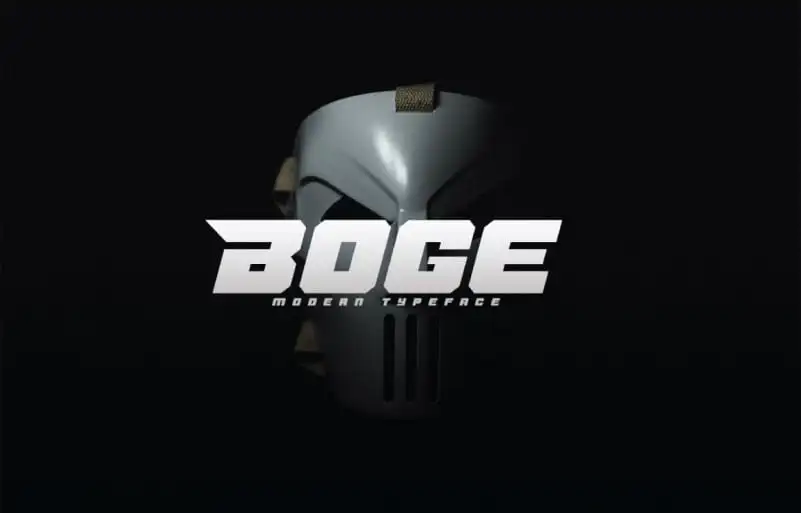
Boge Display Font – Download Grátis
Boge Display Font é uma elegante seleção para aqueles que buscam adicionar um toque distinto a seus projetos digitais. Esta fonte em estilo display é notável por seu traço bold e itálico, com ângulos aguçados que criam efeitos dinâmicos e vibrantes. Com ligaturas personalizadas, esteve concebida para fornecer inúmeras possibilidades de design, sendo especialmente apropriada para trabalhos como cartazes, logotipos, marcações, capas, bandeiras e cabeçalhos. A fonte também se destaca em trabalhos maiores e artesanato, como estampas de camisetas ou obras de arte grande escala. Perfectamente adaptável a uma variedade de necessidades, Boge Display Font é o seu parceiro ideal para transformar qualquer texto em um elemento visual vibrante e único.